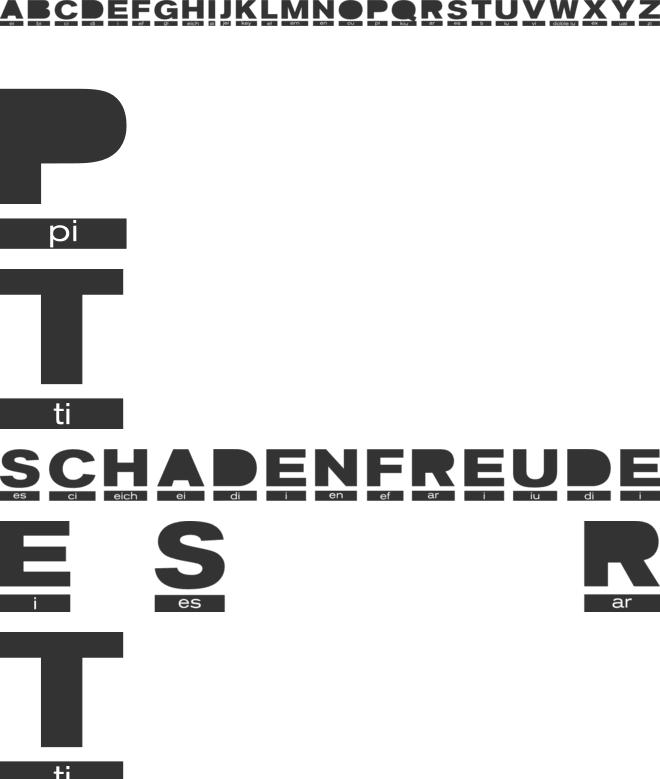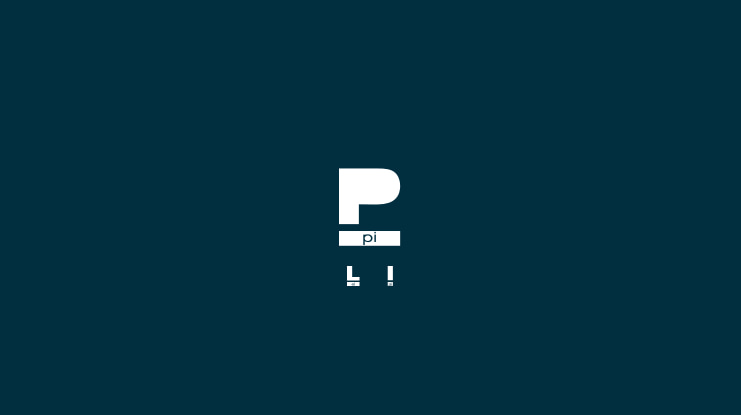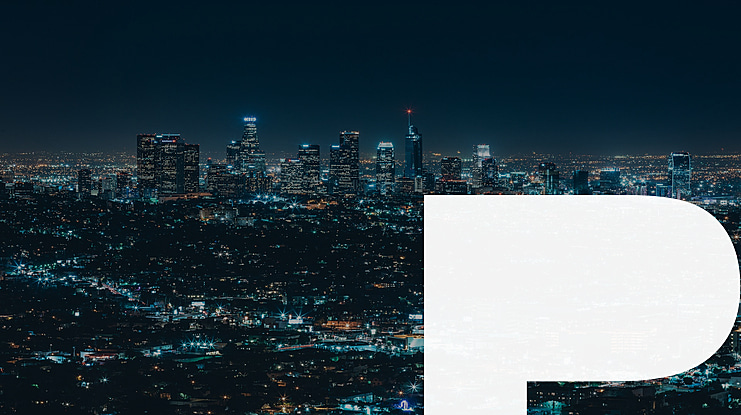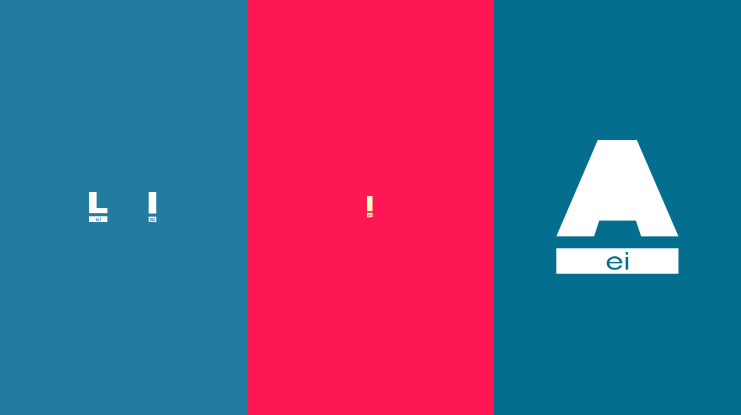
Phonetic Font
Tipografia en la cual se describe foneticamente como se dice cada letra, su uso puede ser educativo o meramente gráfico. (versión ingles)